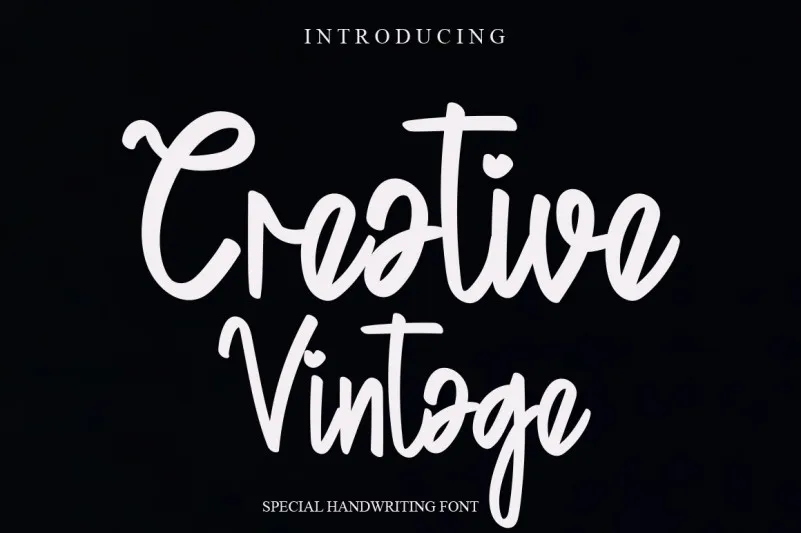
Creative Vintage Script Font – Download Grátis
Esta é uma fonte escrita a mão única, divertida e amigável que traz vida para seu projeto de design. Ideal tanto para aqueles desejando aplicar sua beleza ao Instagram quanto para quem busca um script chamativo para projetos DIY, esta font pode transformar qualquer ideia criativa em um verdadeiro trabalho de arte! Perfeita para designers e criadores de conteúdo que buscam um toque único e pessoal nos seus trabalhos digitais, esta Creative Vintage Script Font leva o seu design ao próximo nível. Composta por traços elegantes e detalhes encantadores, é perfeitamente adequada para criar layouts atraentes ou artigos decorativos que exprimam sua personalidade única. Seja você um designer de gráficos, uma editora especializada em estilo gráfico ou simplesmente alguém apaixonado pela arte digital, esta fonte é o atalho ideal para transformar suas ideias imaginativas e criativas em realidade visualmente impressionante. Descubra como ela pode dar vida à sua imaginação através de uma variedade de projetos, desde artigos gráficos até decoração pessoal.